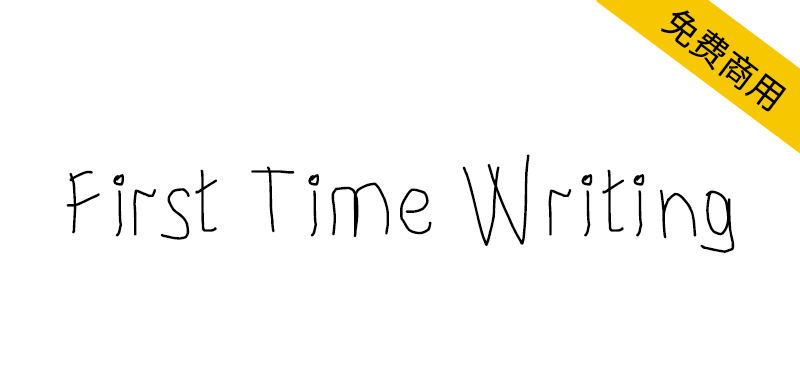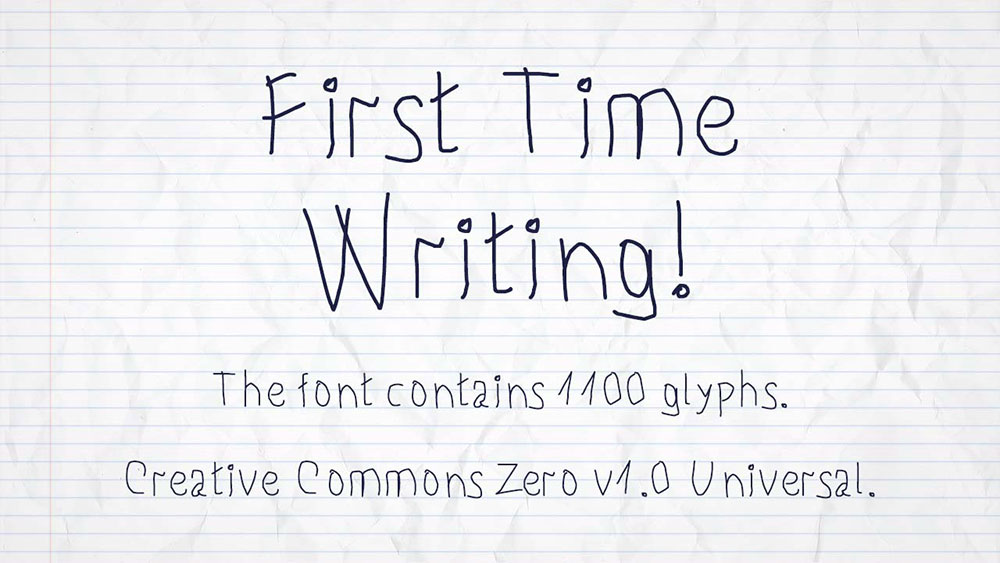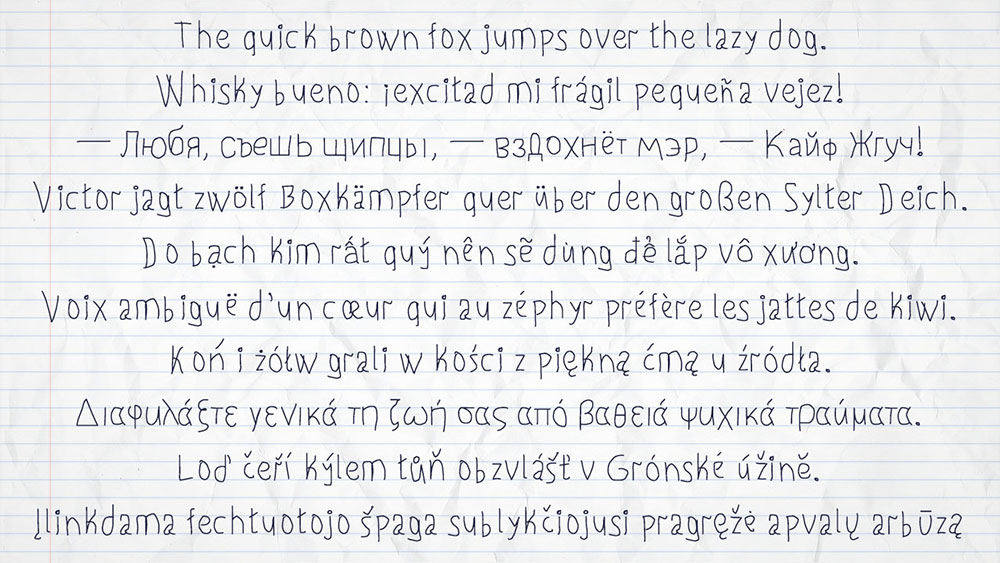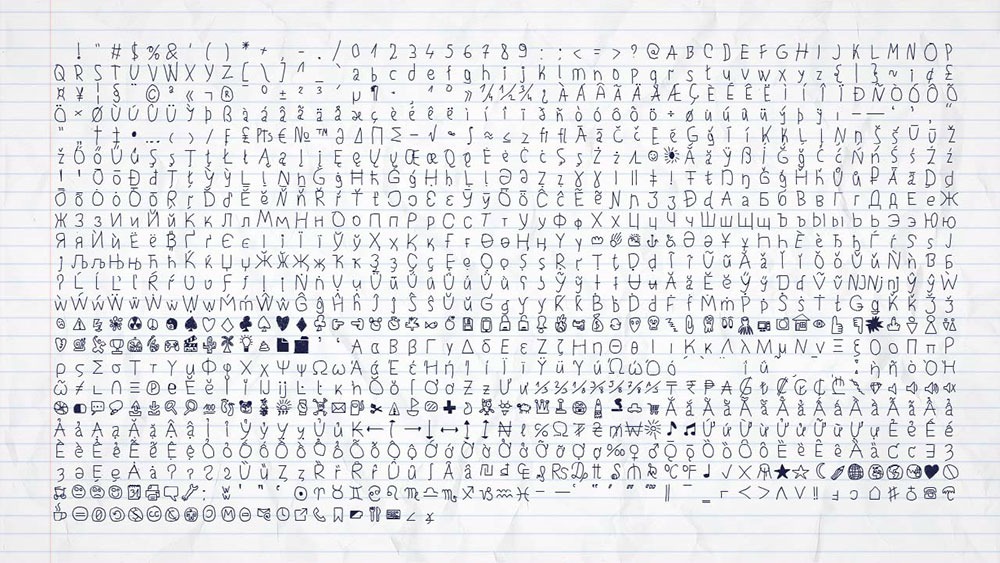
First Time Writing是一款根据CC0协议发布的免费英文字体,手写风格,很像小学生刚练习写字时的风格,包含1100 个字形。
支持 102 种语言:Aghem, Aja, Akan, 阿尔巴尼亚语, Aromanian, Asturian, Azeri, Basaa, Bashkir, 白俄罗斯, Breton, 保加利亚语, Catalan, Central Yambasa, 中文(拼音), Chuvash, 克罗地亚语, 捷克语, Dagbani, 丹麦语, Dinka, Duala, Dutch,英语, 世界语, 爱沙尼亚语, Ewe, Ewondo, 芬兰语, Fon, 法语, Fula, Gagauz, 德语, 希腊语, 瓜拉尼语, 豪萨语, 匈牙利语, 冰岛语, 伊博语, 印度尼西亚语, 爱尔兰语, 意大利语, Jula, Kabyle, Kako, 哈萨克语, Khoekhoe, Koyra Chiini, Koyraboro Senni, 吉尔吉斯语, Lakota, 拉丁语, 拉脱维亚语, Lingala, 立陶宛语, Livonian, Maasai, 马其顿语, 马耳他语, Mapudungun, 马绍尔语, 蒙古语, Mundang, Navajo, Ngiemboon, Ngomba, Northern Sami, 挪威语, 波兰语, 葡萄牙语, Riffian , 罗马尼亚语, 俄语, 苏格兰盖尔语, 塞尔维亚语, 塞尔维亚语, Shawiya, Shilha, Skolt Sami, 斯洛伐克语, 斯洛文尼亚语, 西班牙语, 瑞典语, 他加禄语, 鞑靼语, Tlapanec, 土耳其语, 土库曼语, 乌克兰语, 乌兹别克语, Vai,越南语、瓦尔泽德语、威尔士语、西弗里斯兰语、约鲁巴语、扎尔马语、扎扎基语、祖鲁语。